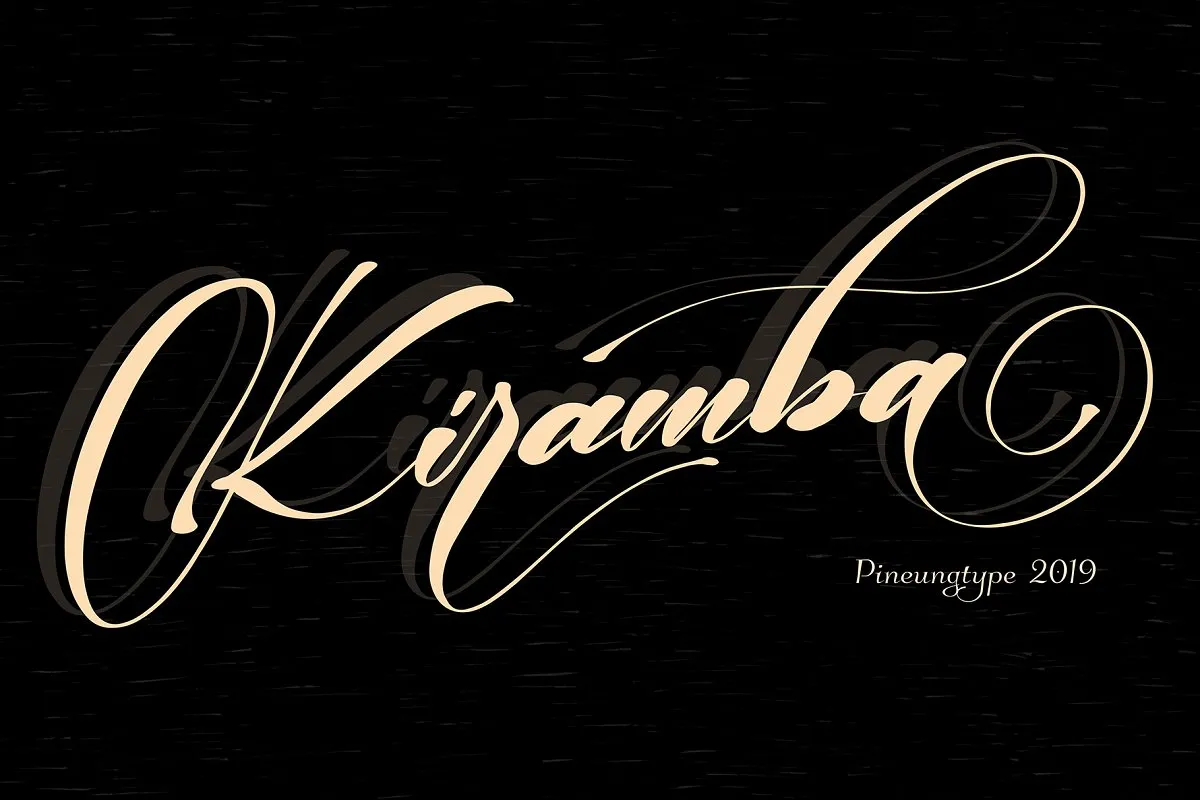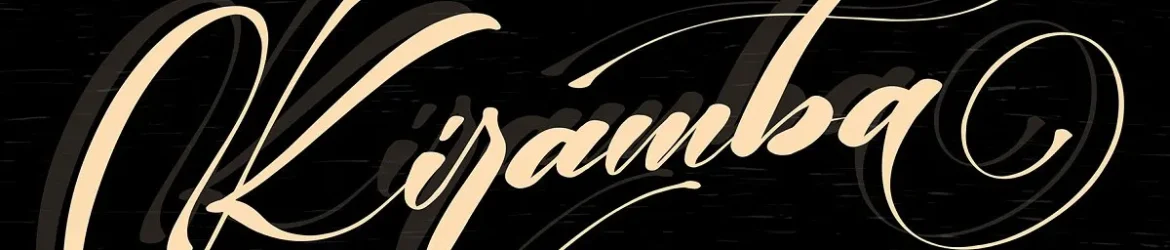
A Kiramba Calligraphy Font é uma fonte elegante que oferece um estilo moderno de escrita chamada. Ela foi criada pelo designer Pineungtype e está disponível gratuitamente no Creativemarket. A Kiramba é perfeita para uma variedade de projetos, desde o design de logotipos até a criação de cartazes e anúncios personalizados. Suas linhas leves e fluidas garantem um toque refinado em qualquer projeto. Seja para adicionar algum texto interessante ao seu site ou blog, criar uma campanha publicitária, ou mesmo fazer uma mensagem especial para sua festa de aniversário, a Kiramba vai se adequar perfeitamente. Além disso, essa fonte é ótima para design gráfico, como letras personalizadas para cartões de convite e papelaria. Seja qual for o seu projeto de design, a Kiramba Calligraphy Font pode ajudá-lo a criar uma identidade visual incrível.